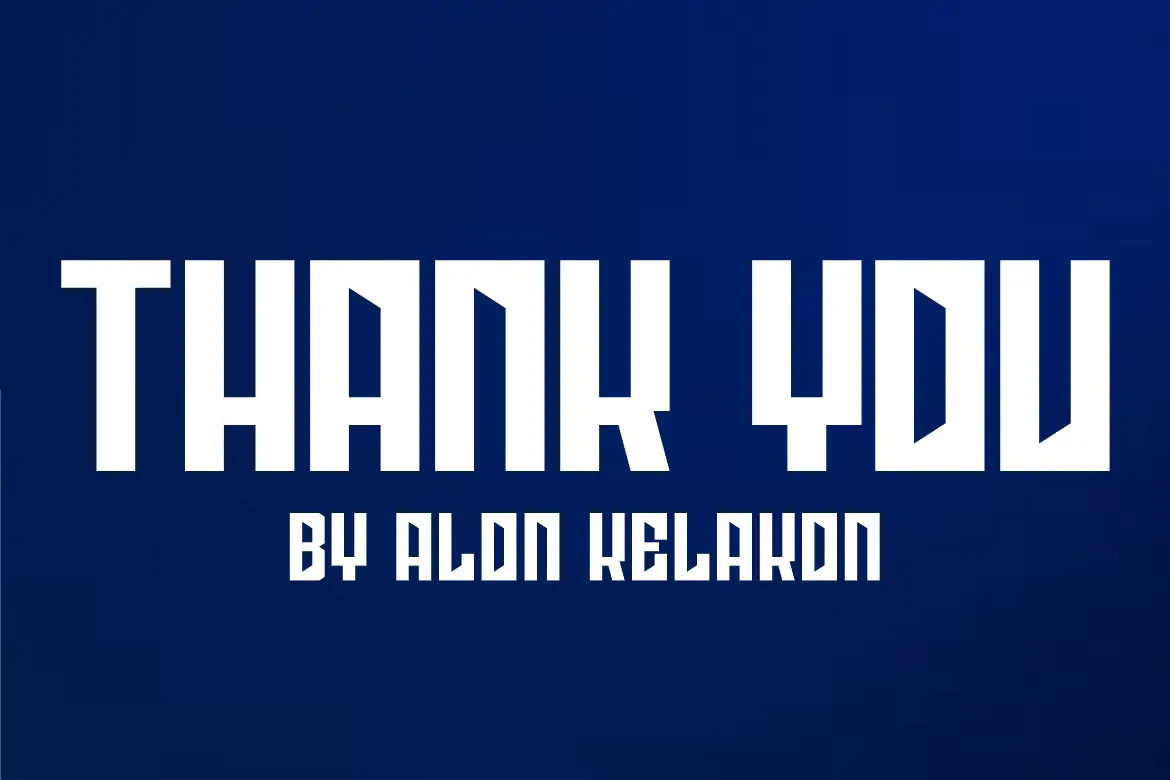
فونت هندسی Spear Ngopreng
فونت هندسی انگلیسی
فونت هندسی Spear Ngopreng یک قلم انگلیسی زیبا و خلاقانه است که میتوان از آن در طرح و پروژههایی همچون طراحی پوستر، کاور آلبوم موسیقی، بسته بندی محصولات، تراکت، کارت ویزیت و … استفاده نمود.